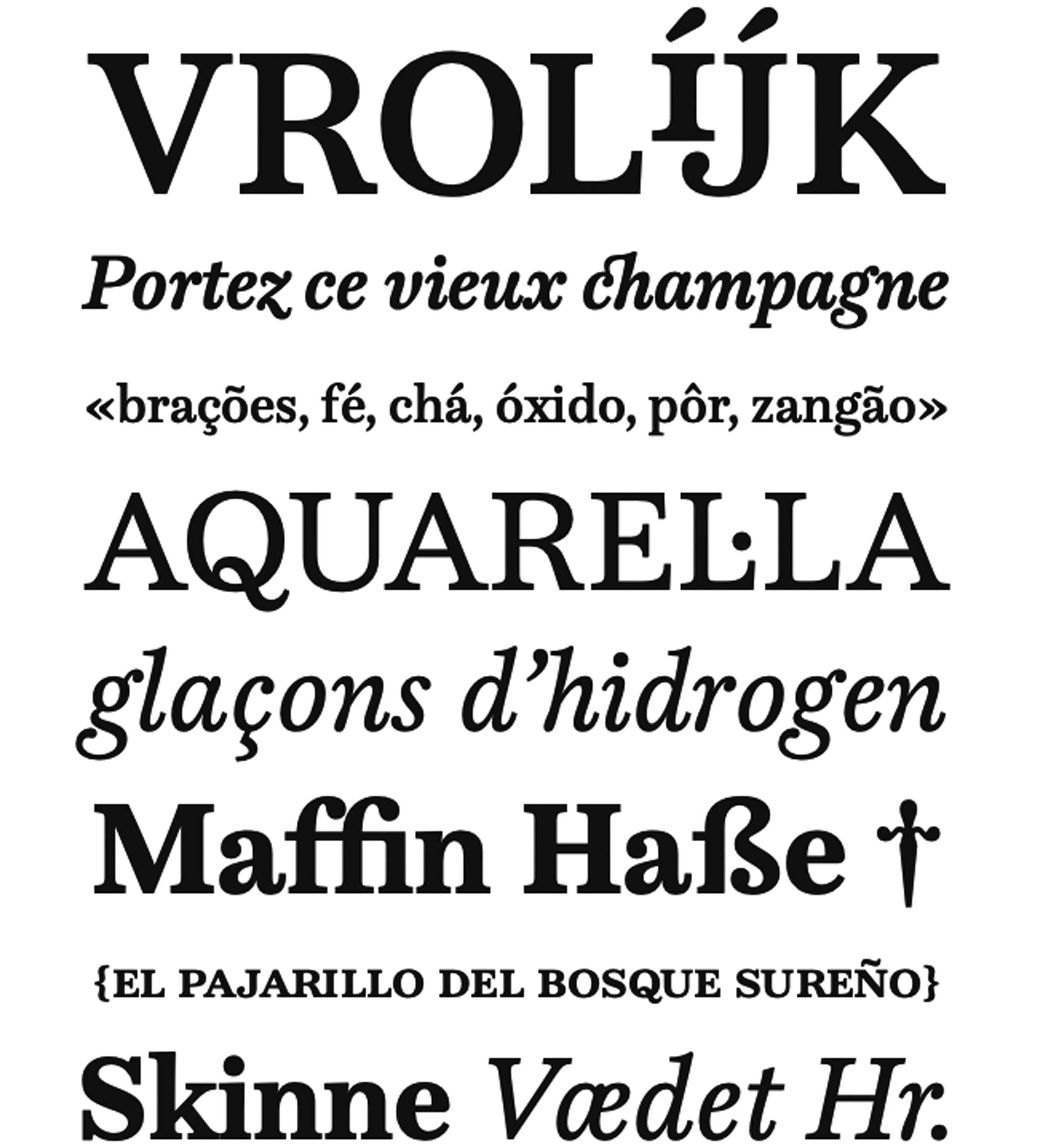
| Descripción | Gotta inicia como proyecto final de Marcela Aguilera en el Máster de Diseño Tipográfico de la Escuela EINA (Universidad Autónoma), en Barcelona.Es una interpretación de la fórmula de las Scotch Romans, a la que se incorporan diferentes influencias Modernas y Transicionales, generando un híbrido de gran interés visual y, al mismo tiempo, una familia tipográfica de alta legibilidad para uso editorial.Contiene características prácticas como small caps y caracteres alternos, y las itálicas destacan por su fuerte acento caligráfico.La última versión ya acabada de la fuente se realizó el año 2023, estando bajo la mirada experta de Josema Urós y Laura Meseguer, de Type-ø-Tones, quienes fueran en su momento los docentes que guiaron el proyecto y hoy se convierten en quienes distribuyen Gotta |
| Clasificación | Texto |
| Familia(s) | Regular, Regular Italic, Medium, Medium Italic, Negrita, Negrita Cursiva |
| Estilos | 6 |